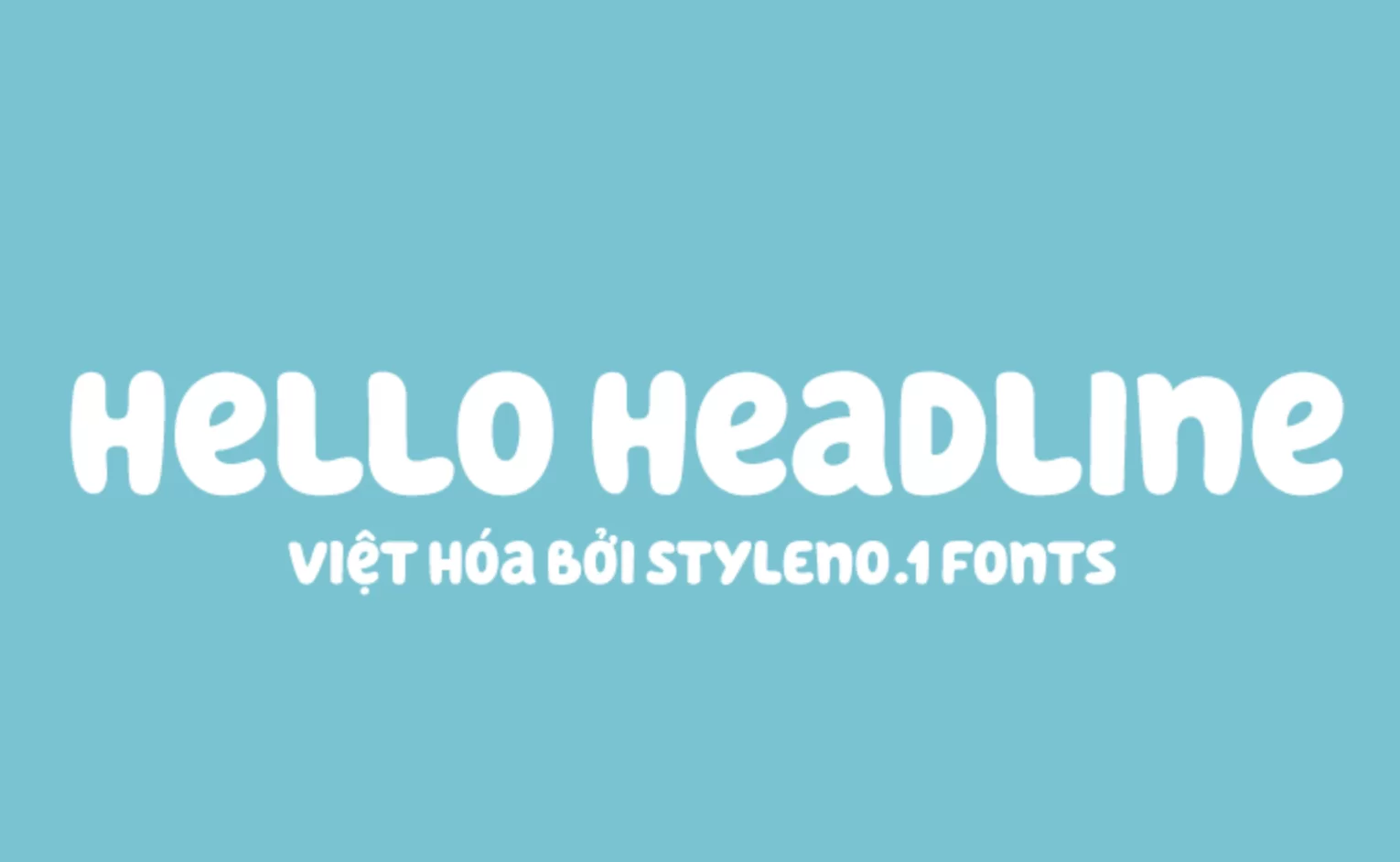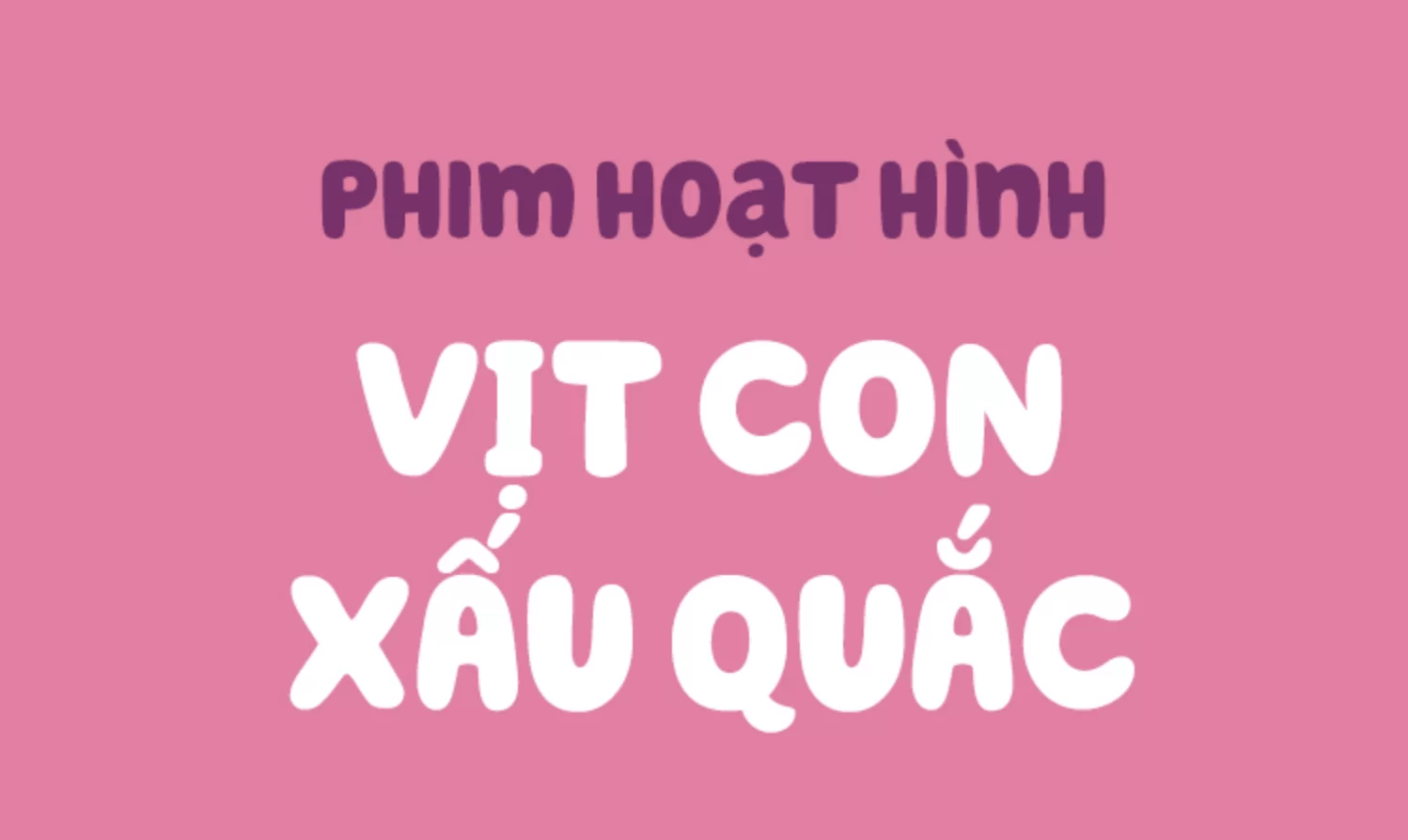
SVN-Hello Headline là một kiểu chữ đậm và thân thiện được thiết kế đặc biệt cho các tiêu đề. Tất cả các chữ cái đều có nét tròn, có lẽ là lý do tại sao chúng có thể nhìn thấy từ xa. Cảm giác tổng thể của kiểu chữ rất vui nhộn phù hợp với thiết kế vui tươi, sự hồn nhiên.
Nhà thiết kế: Veneta Rangelova
Việt hóa: STYLEno.1 Fonts